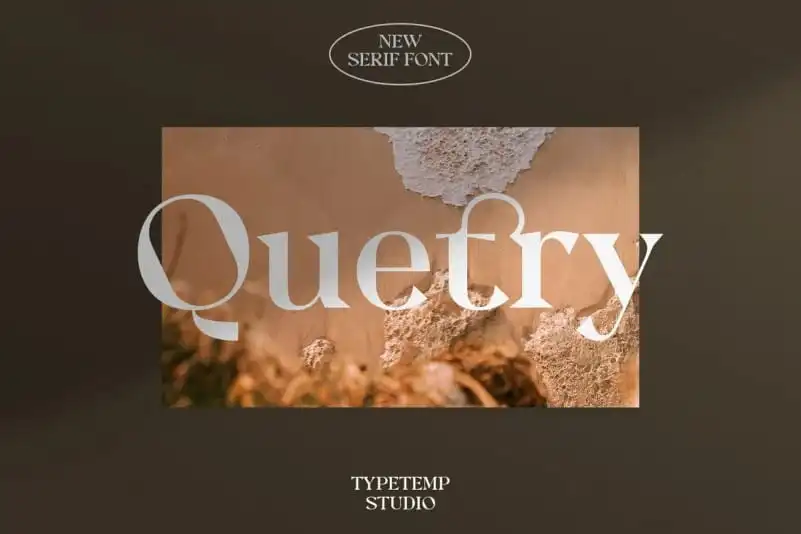
Quetry Serif Font – Download Grátis
Quetry Serif Font é uma elegante tipografia serif capilar criada por Typetemp Studio. O design exuberante desta fonte oferece alternativas e ligaturas que são perfeitas para criar belos logotipos, citações, postagens de blog, projetos de marca, imagens de revistas e convites de casamento, entre outros usos criativos. Com sua elegância sofisticada e acabamento cuidadosamente elaborado, Quetry Serif é uma escolha ideal para quem busca um tipo com o qual criar elementos visuais que se destacam em qualquer plataforma digital ou impressa. Em seu conjunto, a fonte cria um visual profissional e envolvente que vai agradar tanto os criadores de conteúdo quanto designers de marcas.